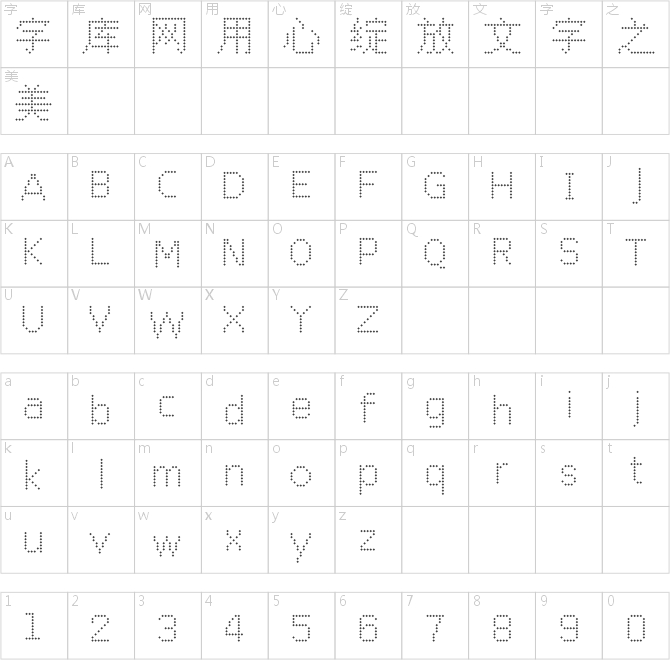
像素
點點像素字體下載DottedSongti
點點中文像素字體是一組基于GPL 2.0協(xié)議開源發(fā)布的中文像素藝術(shù)字體,每種字體均支持超過22000個Unicode字形,覆蓋GBK編碼中的全部簡繁體漢字。
目前發(fā)布的點點像素字體都是基于文泉驛項目所創(chuàng)建的一 種點陣字體衍生而來的。它們是文泉驛點陣宋體經(jīng)矢量化之后,通過變形、美化而得到的。文泉驛點陣宋體是基于GPL 2.0協(xié)議開源的自由字體。請訪問wenq.org以獲取該字體的更多信息。
參考 converter/中的源代碼。該代碼自動將文泉驛點陣宋體中的字型矢量化,然后變形加工為不 同風格的 OpenType 字體。在下載的字體文件包中,包括三個字體文件,主要的區(qū)別是字體的點的形狀不一樣。有三個樣式,一個是圓形的點,一個是方形的點,還有一個是菱形的點。
目前發(fā)布的點點像素字體都是基于文泉驛項目所創(chuàng)建的一 種點陣字體衍生而來的。它們是文泉驛點陣宋體經(jīng)矢量化之后,通過變形、美化而得到的。文泉驛點陣宋體是基于GPL 2.0協(xié)議開源的自由字體。